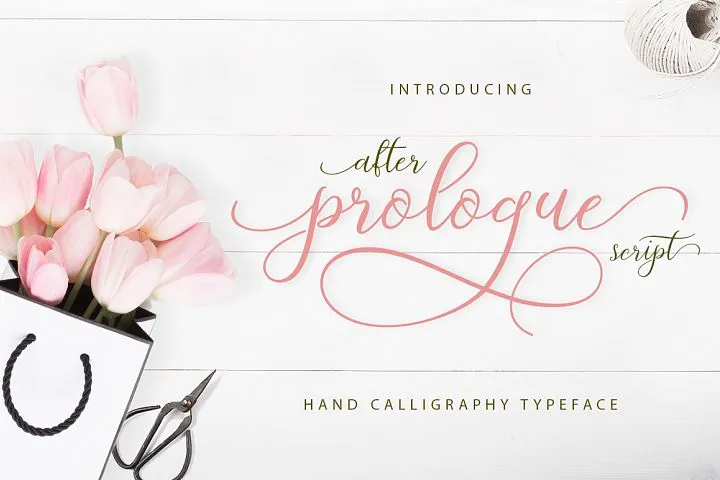
Prologue Script Lite Font – Download Grátis
Prologue Script Lite é uma elegante fonte tipo letra desenhada à mão pelo designer Hamilton. Com seu traçado suave, linha reta fluida e toque clássico, essa fonte estilizada permite um uso versátil em diversas aplicações gráficas. É perfeitamente adequada para headlines, assinaturas, logotipos, convites de casamento, camisetas personalizadas, fundos de papelaria, sinalização e etiquetas. O Prologue Script Lite é uma opção atraente para designers que buscam um toque autêntico em seus projetos, seja para dar um toque sofisticado ou artesanal aos elementos gráficos de seu projeto. Composto por caracteres suaves e elegantes, esta fonte é ideal tanto para aqueles que desejam um toque moderno quanto aqueles que prezam pelo estilo tradicional clássico.